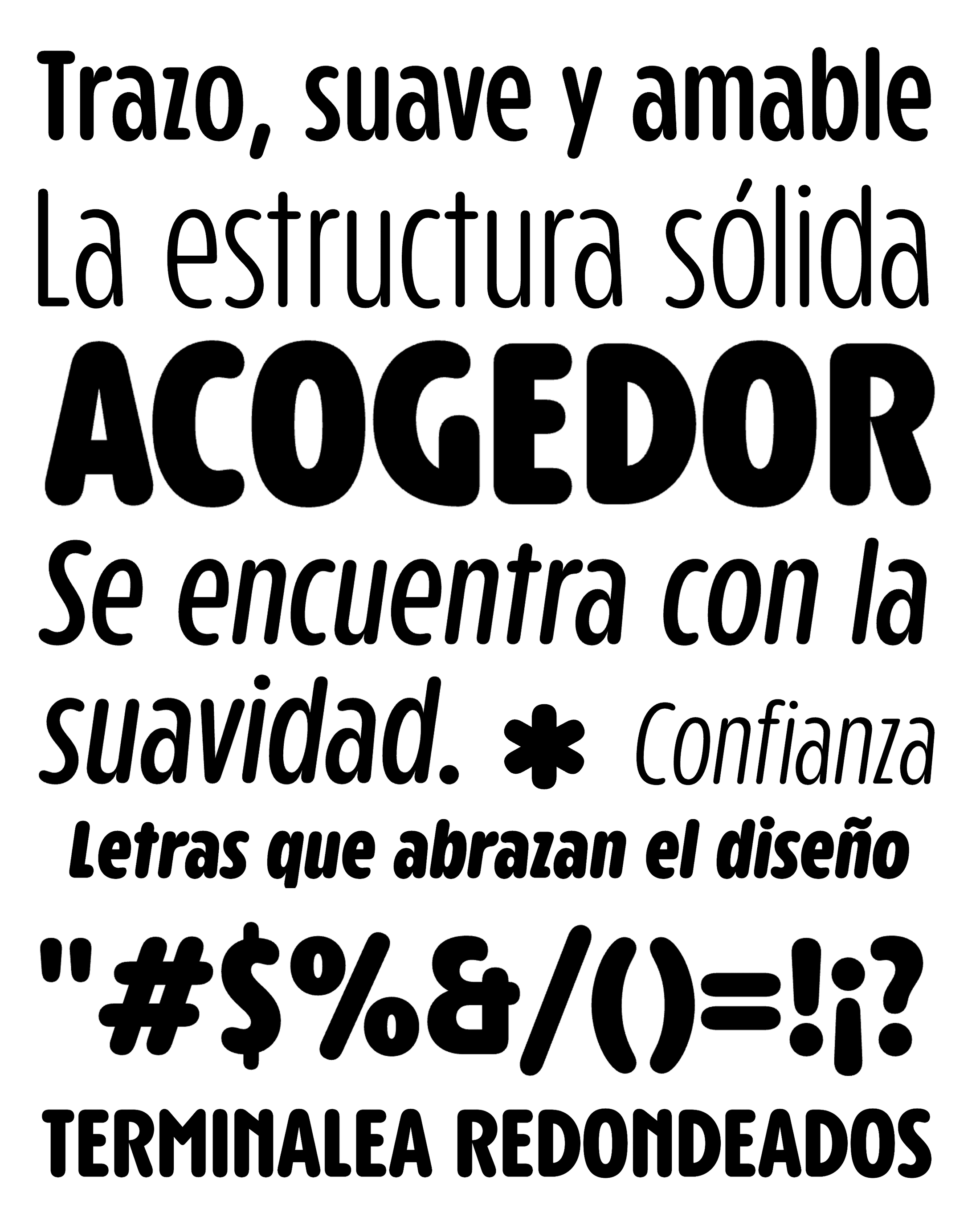
| Descripción | Rosso Rounded es una versión redondeada de la tipografía original Rosso, que ofrece un aspecto distintivo y único. Esta fuente combina el estilo Art Deco con formas redondeadas, convirtiéndola en una opción versátil y atractiva para proyectos que busquen un estilo moderno y amigable. |
| Familia(s) | Rosso, UltraLight, UltraLight Italic, Light, Light Italic, Regular, Regular Italic, Bold, Bold Italic, Black, Black Italic, UltraLight Alt, UltraLight Italic Alt, Light Italic Alt, Regular Italic Alt, Bold Italic Alt, Black Italic Alt |
| Estilos | 10 |